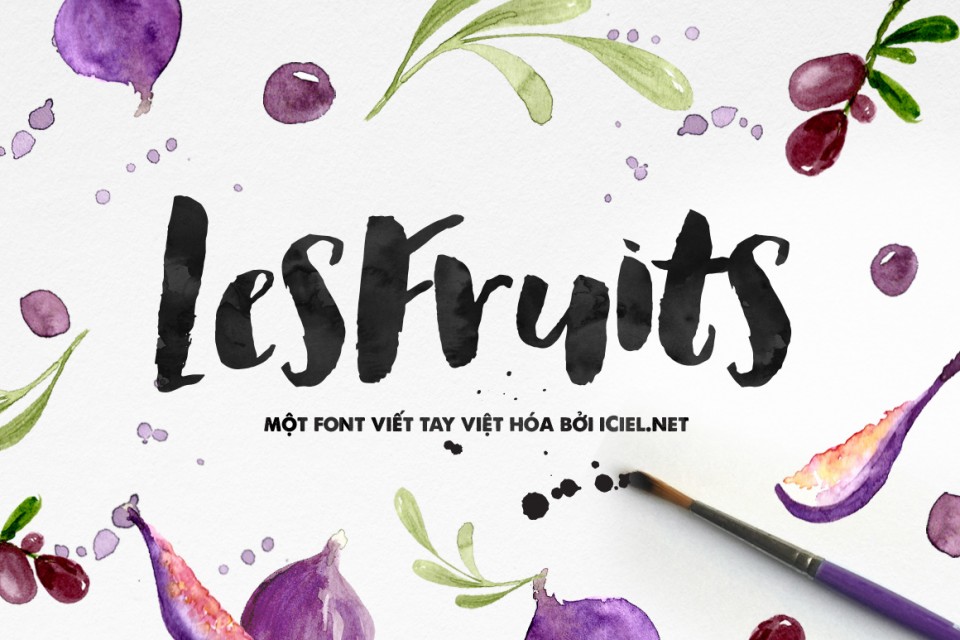
Font việt hóa iCiel Les Fruits
Font việt hóa iCiel Les Fruits – Lựa chọn hoàn hảo cho thiết kế trẻ trung
Giới thiệu về Font việt hóa iCiel Les Fruits
Trong thế giới thiết kế đồ họa, việc tìm kiếm một bộ Font Miễn Phí chất lượng luôn là ưu tiên hàng đầu của các bạn học sinh và sinh viên. Font việt hóa iCiel Les Fruits nổi lên như một hiện tượng nhờ phong cách Brush script đầy phóng khoáng và tự nhiên. Đây là bộ phông chữ được lấy cảm hứng từ những nét vẽ tay mềm mại, mang lại cảm giác gần gũi nhưng không kém phần hiện đại cho mọi tác phẩm sáng tạo.
Đặc điểm nổi bật của iCiel Les Fruits
Bộ phông này sở hữu những đường nét uốn lượn tinh tế, giúp các văn bản tiếng Việt trở nên sống động hơn bao giờ hết. Nhờ quá trình việt hóa chỉn chu, người dùng không còn lo lắng về lỗi dấu hay khoảng cách chữ không đều. Với Font việt hóa iCiel Les Fruits, bạn có thể dễ dàng tạo ra những tiêu đề ấn tượng cho slide bài giảng, thiệp mừng hay các dự án truyền thông học đường đầy màu sắc.
Ứng dụng Font việt hóa iCiel Les Fruits trong học tập và sáng tạo
Đối với môi trường giáo dục, sự sáng tạo luôn được khuyến khích thông qua các bài thuyết trình hay báo cáo nhóm. Sử dụng phông chữ này giúp nội dung của bạn nổi bật hơn hẳn so với các kiểu chữ truyền thống nhàm chán.
Lưu ý khi sử dụng trong thiết kế
Dù mang tính nghệ thuật cao, bạn nên kết hợp Font việt hóa iCiel Les Fruits với các phông chữ không chân (Sans-serif) để đảm bảo tính dễ đọc cho phần nội dung chi tiết. Sự tương phản giữa nét cọ bay bổng và sự gọn gàng của chữ in sẽ tạo nên một bố cục hài hòa và chuyên nghiệp cho sản phẩm của bạn.